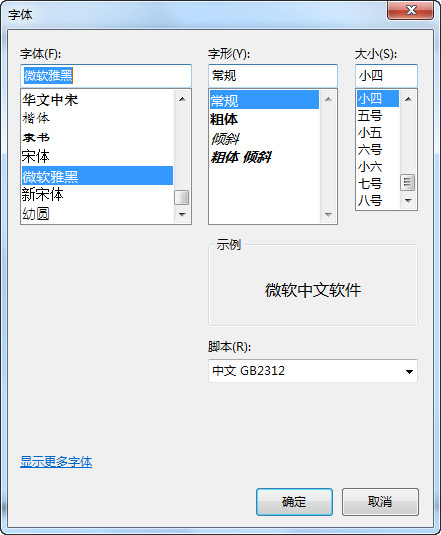
微軟雅黑是美國微軟公司委托中國北大方正電子有限公司設計的一款全面支持ClearType技術的字體。Monotype公司負責字體Hinting工作。它屬于OpenType類型,文件名是MSYH.TTF,字體設計上屬于無襯線字體和黑體。這種字體每個字的造價成本在100美元左右。該字體家族還包括“微軟雅黑Bold”(粗體),文件名為MSYHBD.TTF。這個粗體不是單純的將普通字符加粗,而是在具體筆畫上分別進行處理,因此是獨立的一個字體。微軟雅黑隨簡體中文版Windows Vista一起發布,是Windows Vista默認字體。另外,Microsoft office 2007簡體中文版也附帶這個字體。
在涵蓋的字庫上,微軟雅黑支持GBK字符集,包含了Unicode的所有 20902個中文字符以及中國國家標準化組織添加的大約 80個中文字符,還包含了Big5的繁體中文字符和GB2312中的簡體中文字符。
微軟雅黑體是一款全新的支持 ClearType技術的中文界面顯示字體浮出水面,這就是微軟雅黑體。
這款字體是一種全新的無襯線黑體,它的字形略呈扁方而飽滿,筆畫簡潔而舒展,易于閱讀。這款字體在 ClearType 技術下的清新和優美著實給人留下了深刻的印象。同時,微軟方面也為這種新型字體付出了昂貴的代價。“這種字體每個字的造價成本在100美元左右,據不完全統計,我國各字典、詞海收錄有2萬多個漢字”。
1. 單獨設計的粗體。
2. 顯示品質優異的斜體。
3. 更清晰的小號字顯示。
4. 對于最常用的字號。
5. 更優美而現代的字形設計。